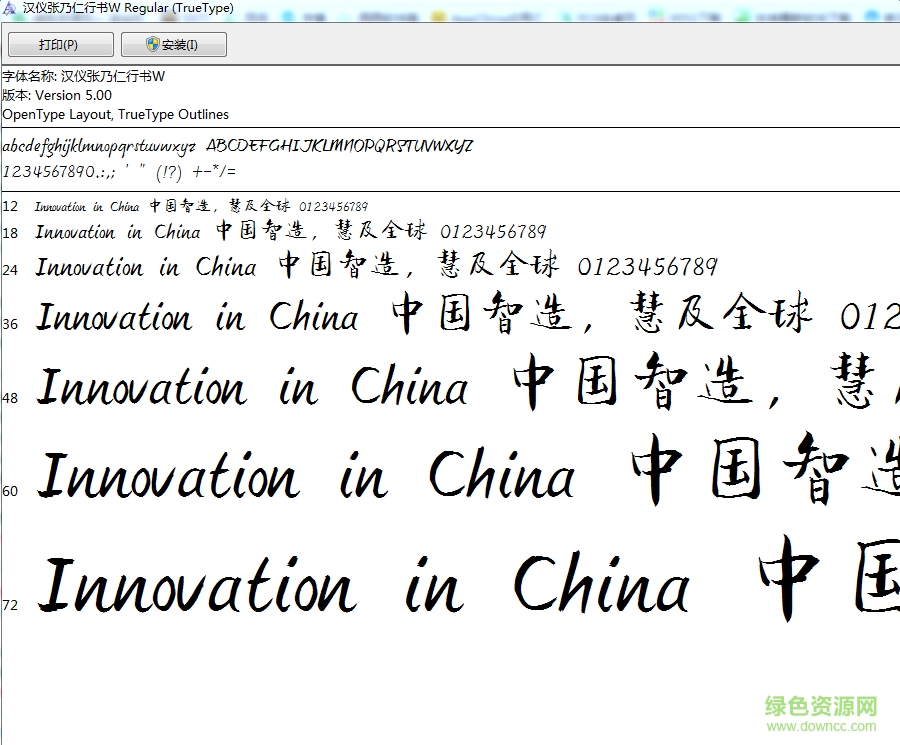
漢儀張乃仁行書字體是一款漢儀類浪漫文雅風(fēng)格字體軟件,張乃仁行書筆畫撇較粗,凸顯其獨(dú)特的行書魅力,整體效果賞心悅目,還有更多類似好看字體歡迎來綠色資源網(wǎng)下載體驗(yàn)!
漢儀張乃仁行書字體是一款應(yīng)用于藝術(shù)設(shè)計(jì)方面的簡(jiǎn)體中文字體,該字體筆畫粗壯,尾部的甩尾有力且有豐富的筆觸細(xì)節(jié),大字效果突出且引人注目;并且最大程度還原作者書寫字形,細(xì)節(jié)表現(xiàn)完整,且字庫(kù)完整,可以廣泛應(yīng)用于名片設(shè)計(jì)、新聞媒體、宣傳海報(bào)、ppt、影視制作以及內(nèi)容用字等領(lǐng)域。
該字體粗細(xì)相間,字體筆畫一氣呵成,行如流水,非常的文雅脫俗,整體效果十分時(shí)尚好看!